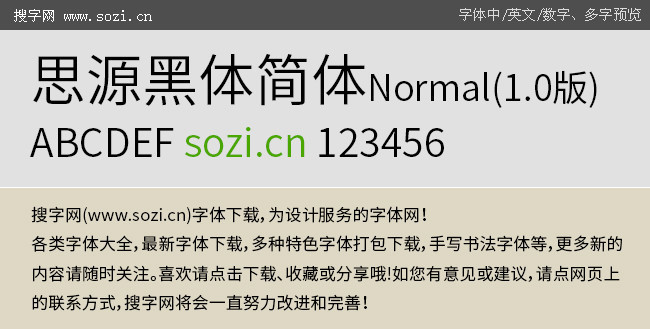
思源黑體簡體Normal1.0
搜字網(wǎng)提供一款思源黑體簡體Normal1.0中文字體下載,思源黑體是一款由谷歌聯(lián)合Adobe發(fā)布全新開源字體,是一款免費、開源黑體字體。可共同呈現(xiàn)一致的視覺美感。本作品適用于書籍排版、報紙排版、畫冊設(shè)計,網(wǎng)頁設(shè)計等應(yīng)用。